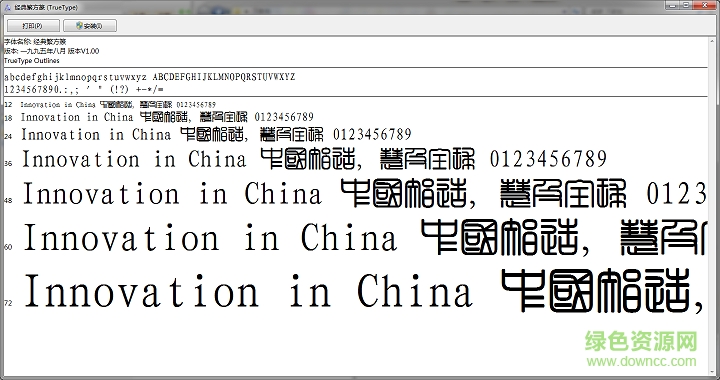
經(jīng)典簡(jiǎn)方篆體
經(jīng)典簡(jiǎn)方篆字體是一款經(jīng)典的篆書字體,字形精美文雅,線條簡(jiǎn)練生動(dòng),可應(yīng)用于廣告設(shè)計(jì)、藝術(shù)設(shè)計(jì)等領(lǐng)域,喜歡的朋友歡迎在綠色資源網(wǎng)下載!